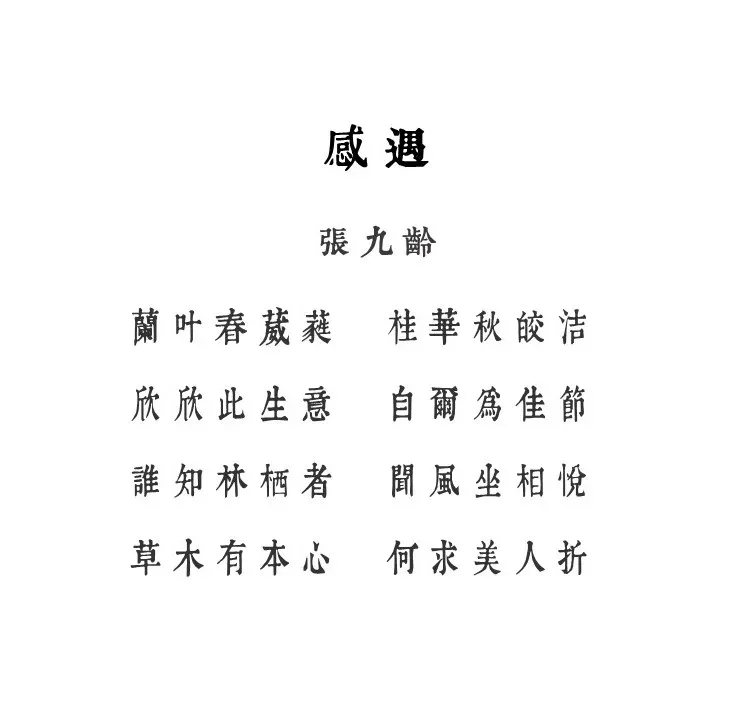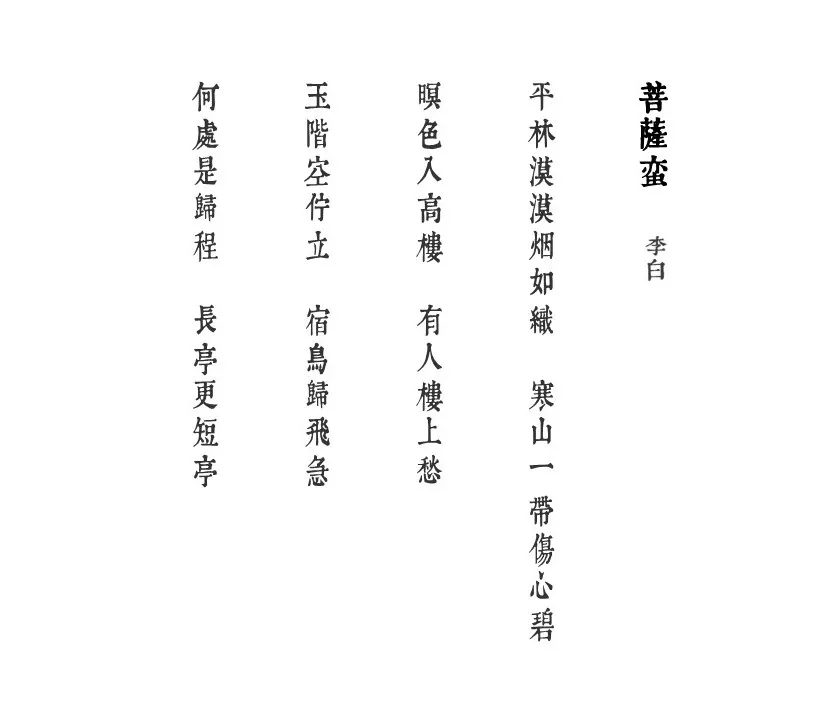
此前,網上有基於康熙字典的字體,康熙字典的字體也是許多文字編輯、平面設計工作者的大愛。不過可惜:其一,網上的康熙字典字體是不可商用的,且當前似乎已不對外提供了;其二,由於康熙字典的雕版古籍,有許多雕版印刷的磨損瑕疵,這些瑕疵一般都沒有得到修復(儘管有古樸殘缺之美,但是也畢竟與雕版原始字的意圖相差甚遠);其三,康熙字典作為繁體字庫,有大量簡體字是沒有的,使用時需要先翻譯成繁體字,而且,還有大量常用漢字沒有對應繁體,也就是說,是完全不被康熙字典包含的。
我們提供的這套字體,基於康熙字典風格進行美化,有以下特點:
1、 拓展了許多康熙字體沒有的字。至少有上百個現代漢語常用字,在康熙字典中是沒有的。潤植家創始人楊博士,按照康熙字體的風格,人工生造而成,這樣,可以用於許多現代語境的詞彙輸入,如“甭說”的“甭”、“垃圾”的“垃”、“多肽”的“肽”、“咖啡”的“咖”、甚至我們讀者受眾多是戲曲愛好者,戲曲中常見的“嗩吶”的“嗩”、“掭頭”的“掭”,等等,大量的字並非繁體簡體互換的問題,而是這些字根本就不存在於康熙字典之中。這類字都得到了生造補充。
2、印刷斑駁噪點充分修復。網上關於古籍的襯線字體,往往存在問題是:雕版印刷斑駁,破損噪點眾多,但沒有得到修復。我們這個字體對康熙字典進行了的斑駁修復,字體整潔如新。
3、美化處理:適當加粗美化,更端莊大氣,適合字少的場景,比如作為海報標題使用。
4、美化處理:適當柔化筆觸,增加一點點書法風格,弱化了一點康熙字典的金石刀篆風格,看起來更賞心悅目一點。
5、部分字形不美觀的字,重新調整字形。
6、我們已為用戶設置成自動轉換繁體,不用再特地將簡體轉化繁體,直接輸入簡體,即可顯示成康熙字典中對應的繁體字,使用更為方便。
潤植家康熙字典美化體正常款(也就是Regular款):常規使用,各種場景適應性好,尤其適合標題、少量文字的海報等。
潤植家康熙字典美化體清瘦款(可以視同Light款):作為輔助,或應用於重要的正文。
用於詩詞類場景(標題為正常款、正文用清瘦款)如下
用於詩詞古文豎排場景(標題為正常款、正文用清瘦款)如下